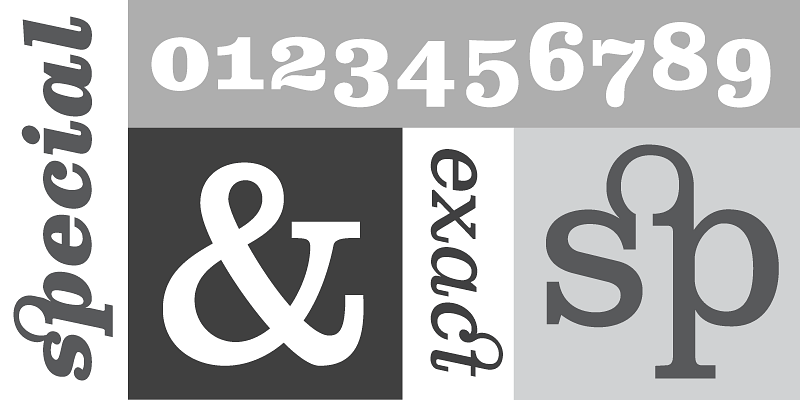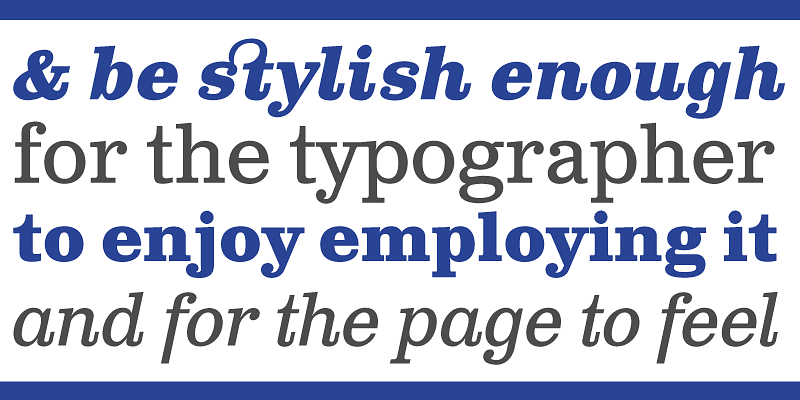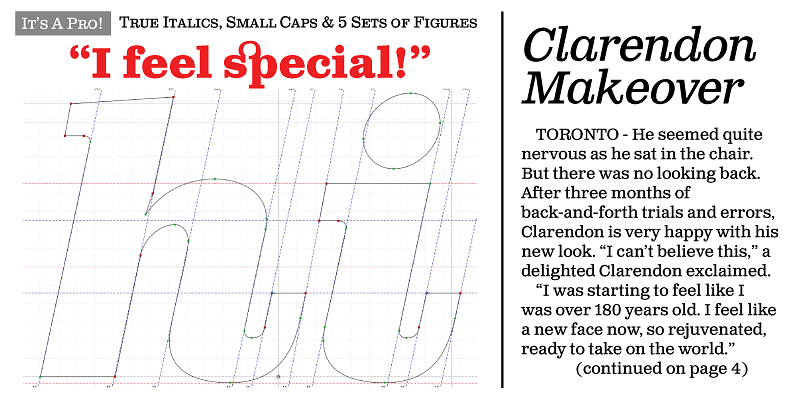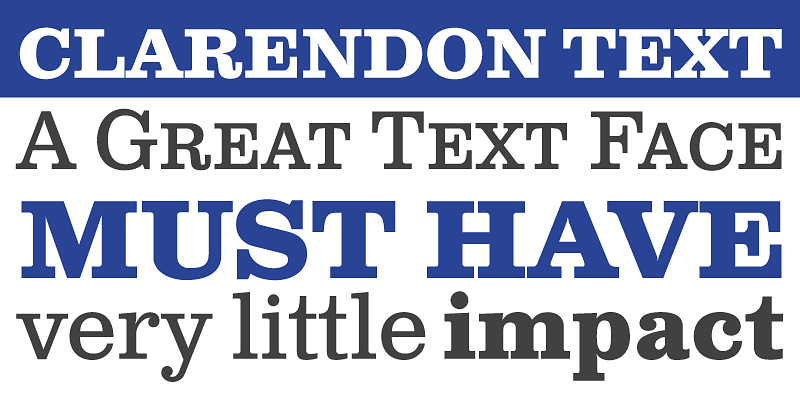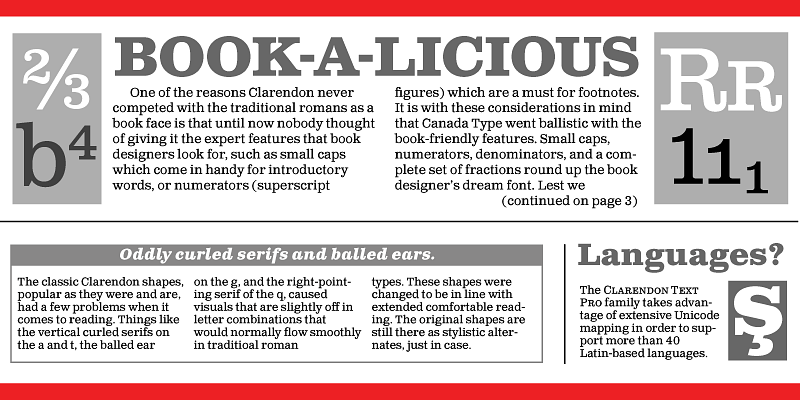
Clarendon Text ist eine zeitgemäße Neuauflage der klassischen Slab-Serif-Schrift, die sich durch eine klare und gut lesbare Schrift auszeichnet. Es handelt sich um eine weithin verwendbare Textschrift, die sich für Distinktion und Stil eignet, ohne die Lesbarkeit zu beeinträchtigen.